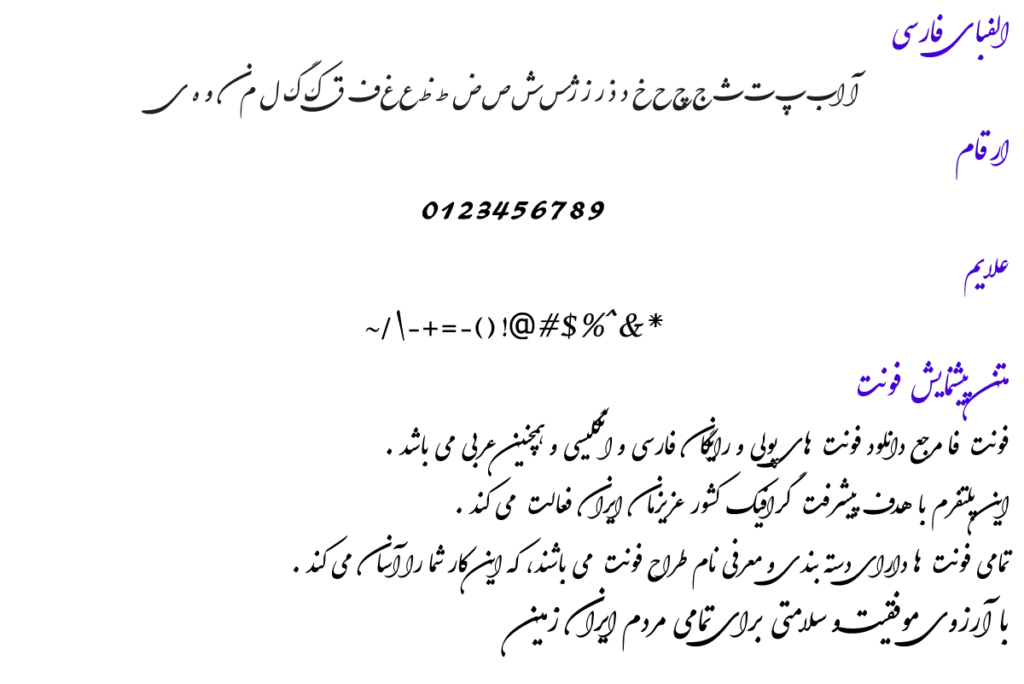
فونت فارسی نستعلیق دیما شکسته – Dima Shekasteh
سال ساخت فونت: 1400
طراح فونت: روح الله بلوردی نوع فونت: فونت خوشنویسی
پیشنمایش فونت نستعلیق دیما شکسته
توضیحات و معرفی فونت نستعلیق دیما شکسته
فونت فارسی نستعلیق دیما شکسته ( Dima Shekasteh ) از مجموعه فونت های آزاد می باشد و نیز نوع فونت خوشنویسی می باشد.
فونت خوشگل مربوط توسط روح الله بلوردی در سال 1400 طراحی و ساخته شده است.
این فونت همانند فونت ایران نستعلیق می باشد ولی با کمی تفاوت!!!
شعر زیبا و قدیمی نام جاوید وطن نوشته با تایپ فیس مرتبط